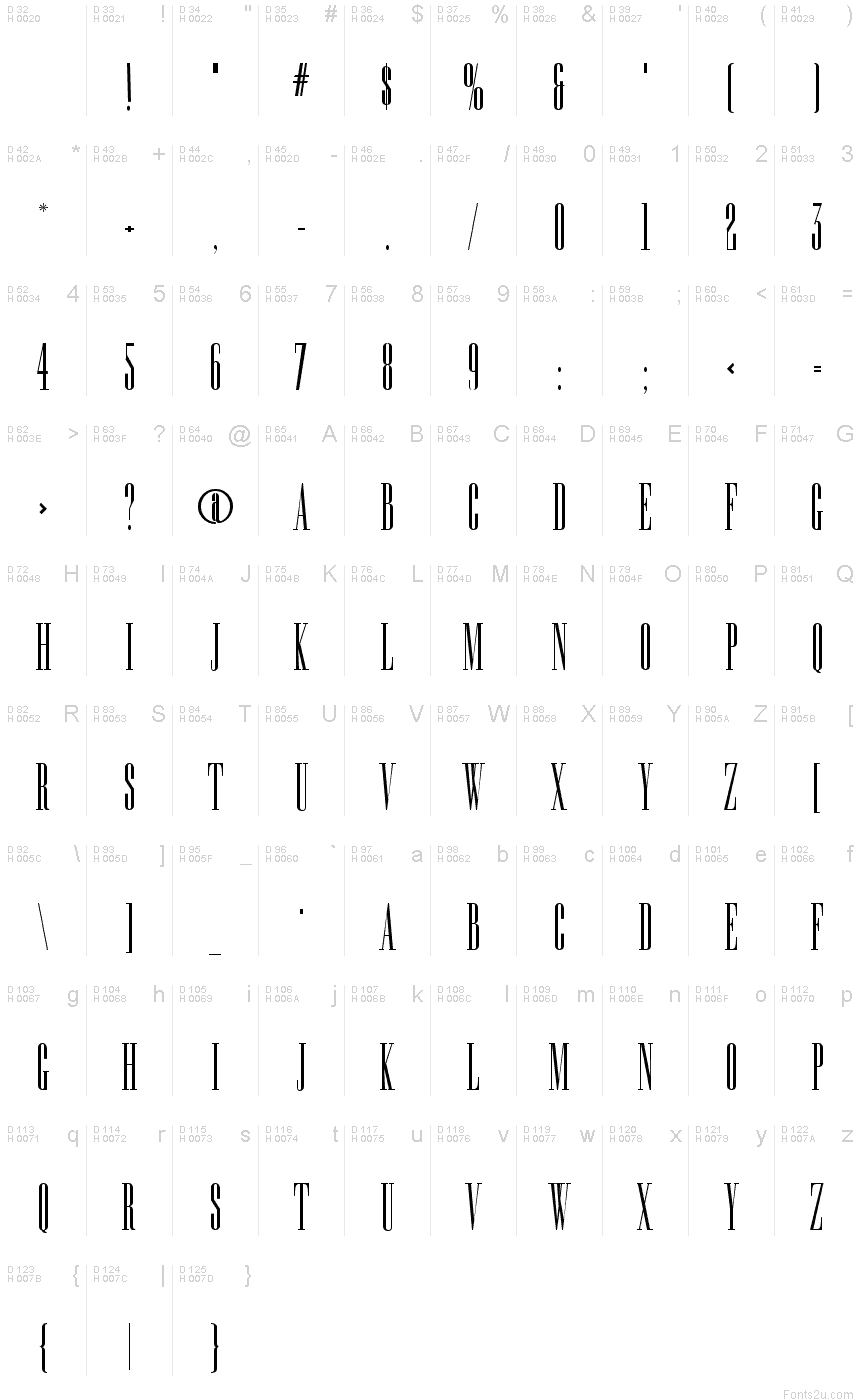
Edition to bezpłatny, ultra-wąski krój szeryfowy o wyrazistym, redakcyjnym charakterze. Jako część rodziny Edition, układa wysokie, smukłe litery w ciasne kolumny, nadając każdemu słowu styl ekskluzywnego magazynu. Kreski są wyraziste i eleganckie, dzięki czemu nagłówki zyskują pewność siebie godną wybiegów mody, zachowując przy tym doskonałą czytelność.
Używając Edition, tego bezpłatnego fontu, nadasz okładkom magazynów, lookbookom modowym, luksusowym markom, plakatom, okładkom książek i ekskluzywnym zaproszeniom elegancki, wertykalny rytm, który przyciąga uwagę. Wąskie formy oszczędzają miejsce w poziomie, więc długie tytuły i dramatyczne frazy mieszczą się idealnie bez pomniejszania kroju. Aby uzyskać zrównoważony układ, połącz wyrafinowaną wysokość Edition ze spokojnym, szerszym krojem bezszeryfowym w tekście głównym, a liniom głównym pozwól wybrzmieć w Edition Regular.